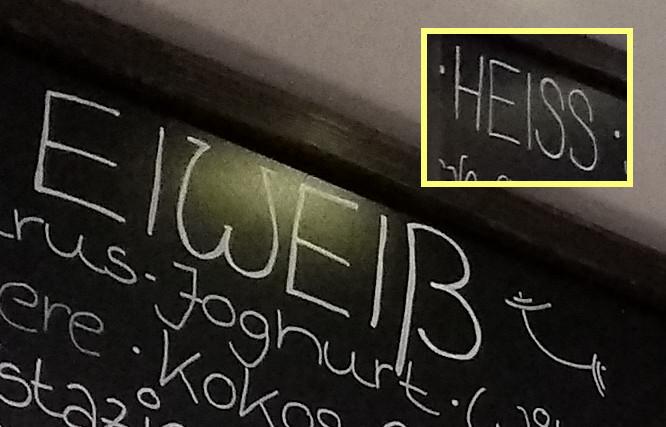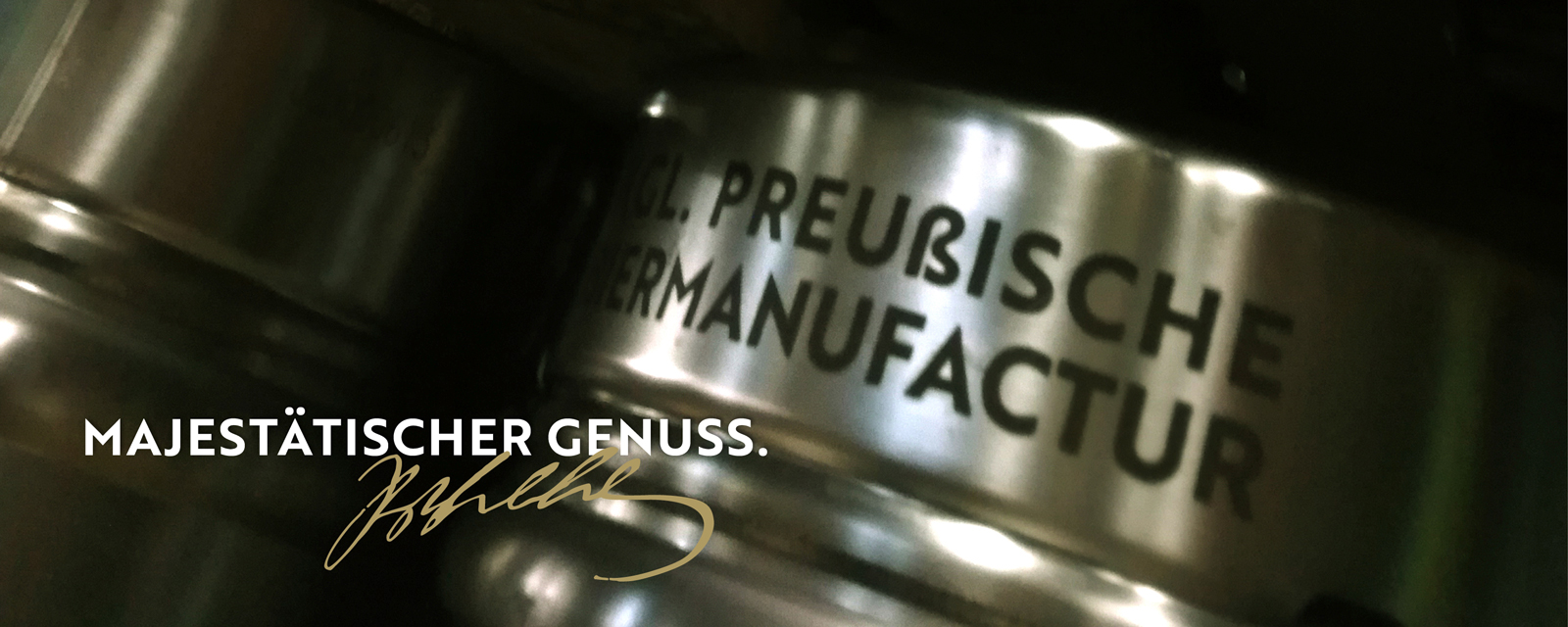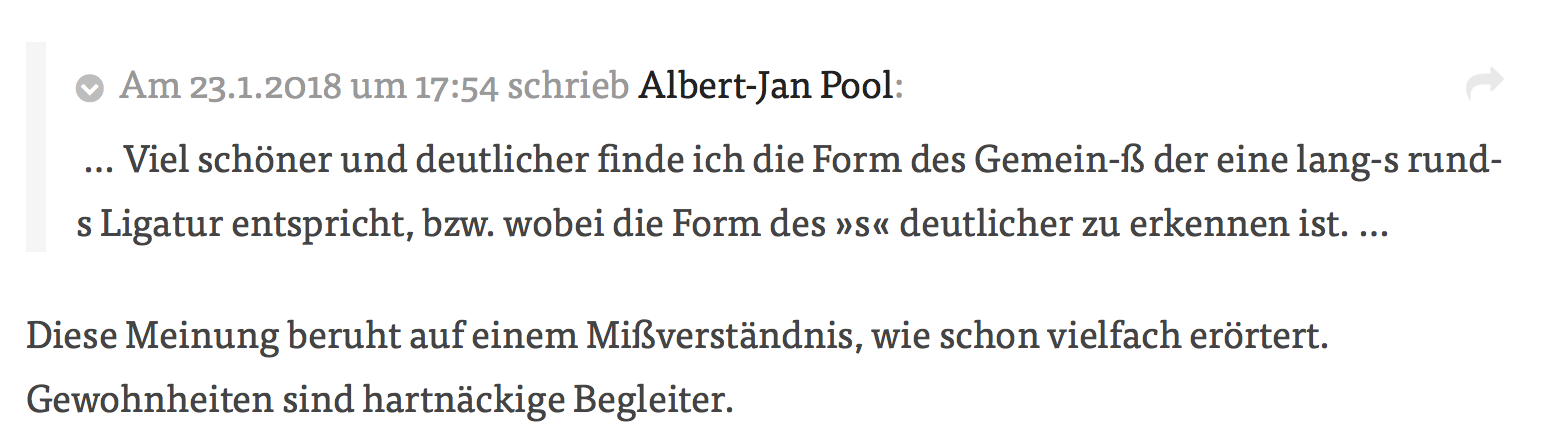
:tuschel: Das sollte der Etikettgestalter mal mit dem Webmaster reden. Auf der Website:
PRINZ VON PREUSSEN … PREUßENS gibt es jetzt auch
Auch inhaltlich ist dieses fürchterliche Marketinggebrabbel nur schwer zu ertragen. Deutschland ist seit 99 Jahren Republik, aber da versucht einer aus seinem »königlichen« Namen Kapital zu schlagen. Mehr ist da nicht. Von Bier haben die Leute auch keine Ahnung. Wer macht heute eine
Bier­ma­nu­fak­tur (ich nehme mal an, dass soll die deutsche Entsprechung von craft brewery sein) auf und bringt lediglich ein einziges Bier heraus, ausgerechnet ein garantiert verwechselbares Massenpils (mit Hopfenextrakt und so)? Es fällt mir ehrlich gesagt schwer, das für echt zu halten und keine Satire.
Über die Möglichkeit, etwas schön oder passend zu finden, wurde gar nichts gesagt. Der Zusammenhang mit einem (historischen) Mißverständnis wurde lediglich festgestellt, nicht unterstellt.
Soviel zum Stichwort Logik.
Haha! Statt Einsicht oder einfach Schweigen,soll der aufgezeigte Logikfehler nun auch noch mit einer Lüge verteidigt werden? Man muss nur nach oben scrollen, um das zu entlarven. Wer soll darauf reinfallen? Dass es nur um »schön und deutlich« ging, hast du selbst zitiert, um dich dann auf diesen und keinen anderen Satz zu beziehen. Das kann man im Nachhinein schlecht abstreiten.
Nichts in Alberts Satz impliziert zwingend geschichtliche Zusammenhänge und somit auch keine diesbezüglichen Missverständnisse. Und somit bleibt es eine (falsche) Unterstellung, keine Feststellung.
Oder um das Logikproblem deutlicher zu machen:
• Bernd sagt: »ich finde ja das zweistöckige a« schöner und deutlicher als das einstöckige.
• Petra erwidert: Diese Meinung beruht auf einem Missverständnis. Hier ein Link zur Geschichte des a …
Es sollte deutlich sein, dass das eine unsinnige Erwiderung ist.
Na hui, das ist mir neu:
Linotype und Bitstream etwa im Update-Modus?*:-o Das Futura-ẞ sieht sogar ganz vernünftig aus.
* Was ja angesichts ihrer vielen veralteten Fonts mal ein Schritt wäre – zumindest bei den Klassikern, wenn die auch in Zukunft noch verkauft werden sollen.
Mir gefällt es überhaupt nicht. Ich finde, es wirkt wie aus einem völlig anderen Sprach-  bzw. Schriftsystem stammend. Das ist bei der Helvetica zwar nicht so, aber auch hier erscheint mir die Form nicht zu den sonstigen Großbuchstaben passend.
Aha?!* Da geht es mir genau andersherum: die Form bei der Avenir bekomme ich zum Beispiel gar nicht mit der sonst geometrischen Grundstruktur zusammen. Das einzige, was mir bei der Helvetica und Avenir besser gelungen scheint, ist die Breite. Das hat bei der Futura nicht so gut geklappt – und eigenartiger Weise hat das ẞ da auch keinen spitzen Winkel wie das Z. Vielleicht ist es das, was das Futura-ẞ für Dich zu einem Fremdkörper macht?
* Perfekt finde ich es auch nicht, aber für Bitstream-Verhältnisse – denen man ja öfters wenig eigene kreative Kompetenz nachsagt – auch nicht so daneben …
Sehe ich auch so. Hier sieht man m.E. ja gut, wo das Problempotential der Avenir- & Helveticaform liegt. Der »Spieß« mit extrem spitzem Winkel läuft einfach zu. Das Futura-ẞ könnte doch problemlos weniger breit sein, wenn man nur den unteren Bogen etwas eher beenden würde, oder? Dann noch die Z-Spitze rechts oben und fertig!
Wenn es das überhaupt muss. Ich glaube wir sollten die Form jetzt auch nicht nur anhand des oben gezeigten Schriftmusters mit Einzelbuchstaben ohne Wortzusammenhang bewerten. Ich habe schon einige geringfügig breitere Beispiele gesehen, wo mich das im Text kaum gestört hat.
Aber gut – Ihr hartnäckigen ẞ-Form-Kritiker seid mir offenbar ohnehin einen Schritt voraus. Ich freue mich erstmal dass das ẞ überhaupt nach und nach Akzeptanz findet und bei immer mehr Foundries zum Standard erhoben wird und scheue mich eher dieses »zarte Pflänzchen« schon zu sehr zu beanspruchen. ;-)
Zartes Pflänzchen … ich finde, das ist kein Argument in die Diskussion darüber, wie man ein Versal-ß so gestalten kann, dass sie zu einer bestimmten Schrift passt und zugleich als solches erkennbar ist. Ich bin der Meinung, dass letzteres in allen drei Fällen, Avenir, Futura und Helvetica gelungen ist. Bei Avenir und Helvetica passt die Form absolut nicht zur Schrift, sie wiederspiegelt weder den konstruktiven Ansatz der Avenir (Frutigers optisch korrigierte Antwort auf der sehr geometrischen Futura), noch die vertikale Betonung und großzügige Innenformen der Helvetica. Zudem ist der spitze und zulaufende Innenform rechts oben optisch eine Katastrophe. Für mich sieht das Ganze eher aus wie die handwerklich nicht-gekonnte »Modernisierungen« von Altbauten der 1960er und die Baumarkt-Ästhetik der zahllosen Anbauten, Vordächer und Carports in einst architektonisch einheitlich gestaltete Wohnsiedlungen. Tragisch, eigenwillig, hässlich und vor allem Zeugen respektloser Getriebenheit eine fixe Idee hinterher zu rennen und womöglich sich selbst darstellen zu wollen anstatt eine sinnvolle und ästhetisch ansprechende Ergänzung zu einer vorhandenen Formenkanon entwickeln zu wollen. Wenn ich Max Miedinger oder Adrian Frutiger wäre, würde ich mich im meinem Grab umdrehen und mein zartes Pflänzchen beweinen.
Ach, das wird schon. Gerade habe ich das hier im Fitnessstudio (mit angeschlossenem Kinderspielplatz :biglove:) auf einer augenscheinlich von einer Person beschriebenen (sehr langen, deshalb hier nicht komplett gezeigten) Tafel gesehen:
Einige Zeit werden wir noch solche Sachen sehen, aber irgendwann dann nicht mehr.
(Leider gab es auf der Tafel kein [explizites] Minuskel-ß zum Vergleich. »Dummerweise« war das mehrfach angepriesene Fassbier konsistent korrekt geschrieben.)